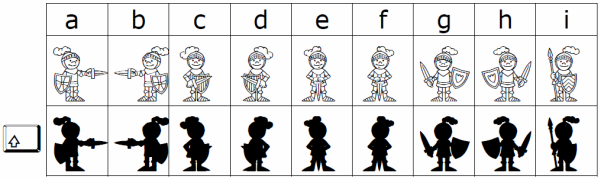
Bilder als Figuren und in Wortfeldern.
Bilder zum Gestalten und Ausschmücken von Arbeitsblättern. Es lassen sich damit auch besondere Arbeitsbögen und Materialien zu „Spiegel-” und „Schattenbilder” gestalten.
Wozu passt das Spiegelbild?
Spiegelbilder
Jeder zweite Buchstabe ist das Spiegelbild zum vorangegangenen:
Es sind in allen Fonts leider nicht alle Buchstaben belegt.
Wozu passt das Schattenbild?
Zur besseren Orientierung gelten daher die folgen Tastaturbelegungen. Die Fonts sollten nicht unter 20 Punkt angewendet werden. Die Darstellung auf dem Bildschirm entspricht nicht immer dem Ausdruck.
Hier nun ein Beispiel des Fonts „Figur Auto”
Hier nun ein Beispiel des Fonts „Figur Geister”
Hier nun ein Beispiel des Fonts „Figur Indianer”
Hier nun ein Beispiel des Fonts „Figur Jungen”
Hier nun ein Beispiel des Fonts „Figur Maedchen”
Hier nun ein Beispiel des Fonts „Figur Prinzessin”
Hier nun ein Beispiel des Fonts „Figur Ritter”
Hier nun ein Beispiel des Fonts „Figur Teddy”
Hier nun ein Beispiel des Fonts „Wortfeld Bad”
Hier nun ein Beispiel des Fonts „Wortfeld Fahrzeug”
Hier nun ein Beispiel des Fonts „Wortfeld Haus”
Hier nun ein Beispiel des Fonts „Wortfeld Kleidung”
Hier nun ein Beispiel des Fonts „Wortfeld Koerper”
Hier nun ein Beispiel des Fonts „Wortfeld Kopf”
Hier nun ein Beispiel des Fonts „Wortfeld Kueche”
Hier nun ein Beispiel des Fonts „Wortfeld Obst”
Hier nun ein Beispiel des Fonts „Wortfeld Spielzeug”
Hier nun ein Beispiel des Fonts „Wortfeld Tiere”
Hier nun ein Beispiel des Fonts „Wortfeld Werkzeuge”
Hier nun ein Beispiel des Fonts „Wortfeld Wohnen”